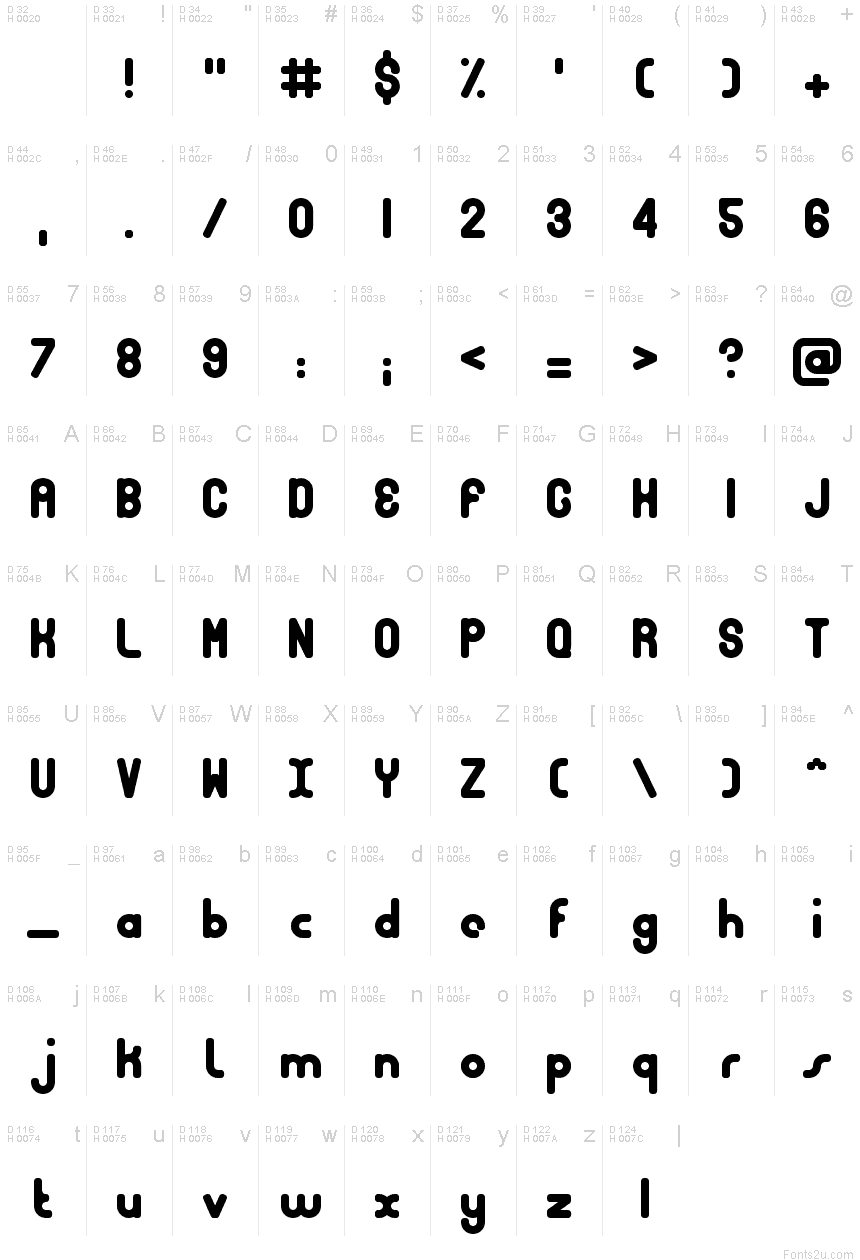
Bubble Club ist eine kostenlose, verspielte Comic-Display-Schrift mit weichen, voluminösen Formen und einem modernen Schwung. Die Buchstaben sind durchgehend dick und abgerundet, mit tiefen Kurven und kompakten Öffnungen – ein Schriftbild, das freundlich, kräftig und fast wie ein Spielzeug wirkt.
Die Schrift passt perfekt auf Kinderposter, Süßwarenverpackungen, Party-Einladungen, App-Splash-Screens oder fröhliche Ladenschilder – überall dort, wo kurze Wörter eine pummelige, lebensfrohe Note brauchen. Als Free-Font eignet sich Bubble Club auch hervorragend für Cover-Texte, einfache Logos und Social-Media-Grafiken, besonders wenn die abgerundete Form der Buchstaben die volle Aufmerksamkeit auf sich ziehen soll.